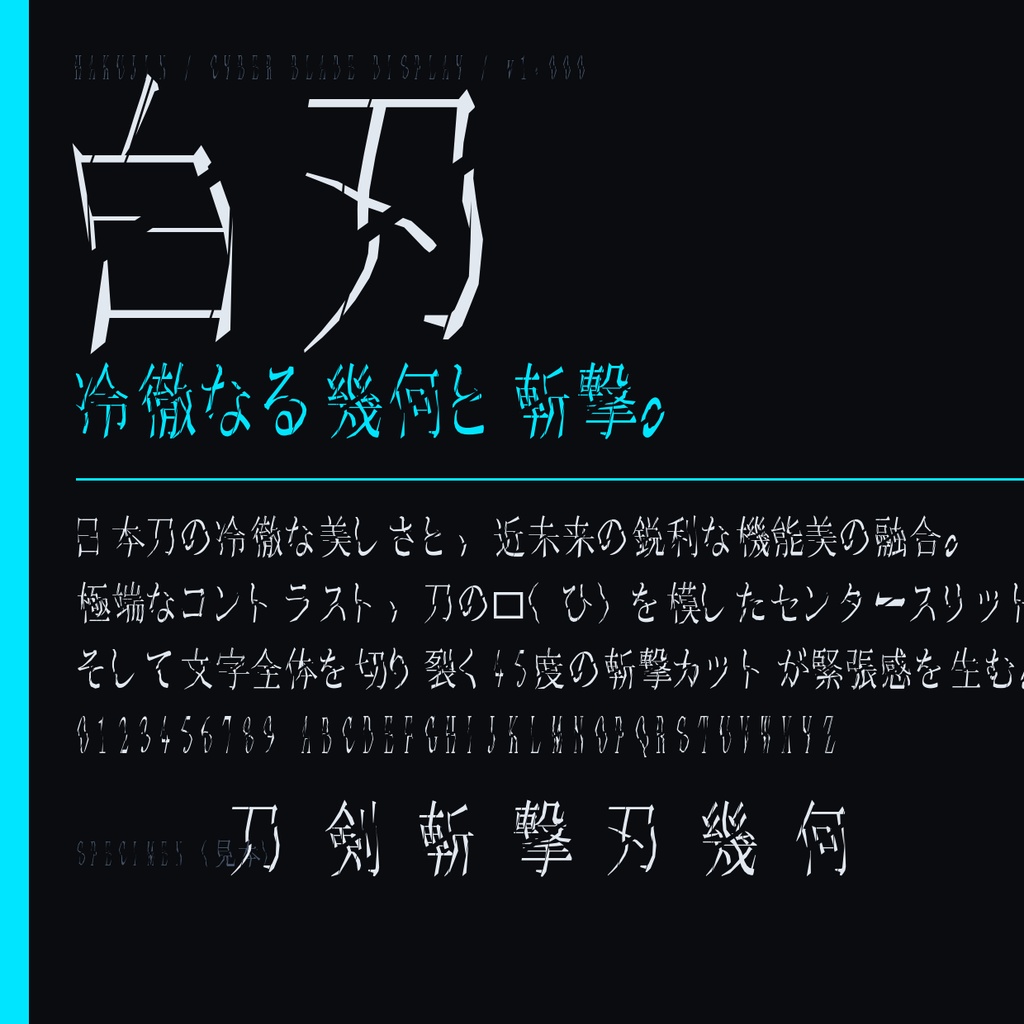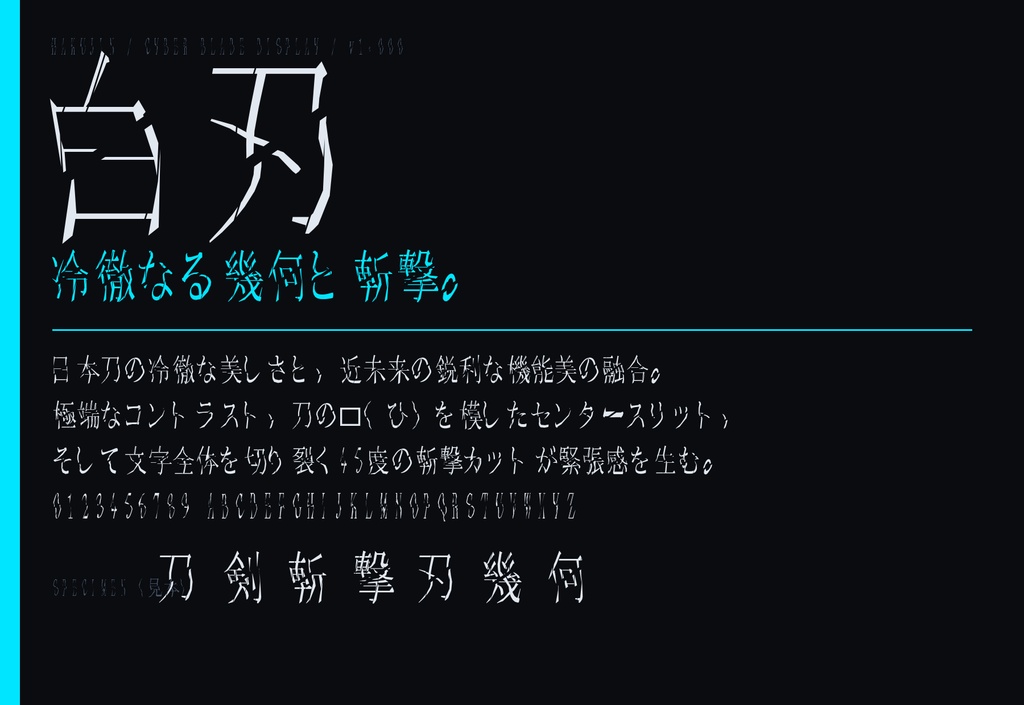
【白刃 / HAKUJIN】刀傷・斬撃風 日本語フォント2書体セット|常用漢字2,136字収録
【白刃 / HAKUJIN】 冷たい刀身の緊張感と、斬撃の瞬間を文字へ刻み込んだ日本語ディスプレイフォントです。 極端な明朝コントラスト、刀の樋を思わせる縦スリット、45度の斬撃カットによって、 鋭く不穏なタイトルを作ります。 標準の「Regular」と、切断・ずれ・荒れを強めた「Egui」の2書体セットです。 ■ 価格 1,280円 ■ 形式 TrueType(TTF) / Windows・macOS ■ 収録 各2,541文字(空白を含む) 常用漢字:2,136字 ひらがな・カタカナ・英数字・全角英数・基本記号 ■ 内容 ・Hakujin Regular:読みやすさを残した刀身スリット ・Hakujin Egui:斬撃のずれと切断を強調した強表現 ■ おすすめ用途 ゲーム・映像タイトル、和風ホラー、バトル演出、配信画面、ロゴ、装丁、同人作品 ■ 利用 個人・商用利用可。ロゴ、動画、ゲーム、印刷、配信、同人・商業作品に使用できます。 クレジット不要です。フォントデータの再配布・共有・転売は禁止です。 詳細はZIP内の利用規約をご確認ください。 ■ 字形由来 字形骨格にはGlyphWiki KAGEデータを使用し、独自のスリット・斬撃・変位処理を 加えて再構築しています。 ※見出し・タイトル向けです。小サイズの本文用途には向きません。 ※Eguiは斬撃が字面外へ伸びるため、文字間隔によって隣接文字と重なる場合があります。